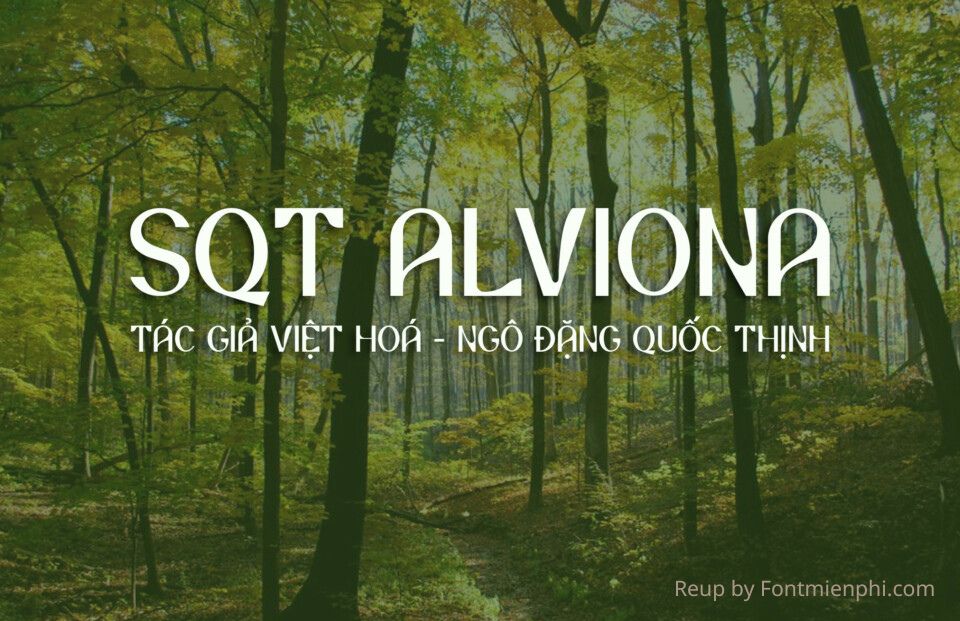
Font Việt hóa SQT Alviona Tải miễn phí font chữ thanh lịch, hiện đại
Font Việt hóa SQT Alviona – Tải miễn phí font chữ thanh lịch, hiện đại
Font Việt hóa SQT Alviona là một mẫu font chữ đẹp mang phong cách thanh lịch, mềm mại và hiện đại. Với đường nét tinh tế, kiểu dáng nổi bật và khả năng tạo điểm nhấn tốt, SQT Alviona rất phù hợp cho nhiều dự án thiết kế sáng tạo như logo, poster, banner, thiệp cưới, ảnh bìa, tiêu đề, bao bì sản phẩm và nội dung mạng xã hội.
Giới thiệu font SQT Alviona Việt hóa
SQT Alviona sở hữu phong cách chữ nghệ thuật, hiện đại nhưng vẫn giữ được nét mềm mại và sang trọng. Font tạo cảm giác nhẹ nhàng, tinh tế, phù hợp với các thiết kế cần sự nổi bật nhưng không quá cầu kỳ.
Phiên bản font Việt hóa đã được bổ sung hệ thống ký tự tiếng Việt, giúp người dùng dễ dàng nhập đầy đủ dấu và sử dụng trong các phần mềm thiết kế phổ biến.
Font có thể phù hợp với nhiều chủ đề như:
• Thiết kế logo thương hiệu
• Thiết kế poster và banner
• Làm thiệp cưới, thiệp mời
• Thiết kế ảnh bìa Facebook, YouTube
• Làm tiêu đề video và thumbnail
• Thiết kế bao bì sản phẩm
• Làm nội dung thời trang, mỹ phẩm, làm đẹp
• Thiết kế bài đăng mạng xã hội
• Làm typography và các ấn phẩm sáng tạo
Điểm nổi bật của font Việt hóa SQT Alviona
Một trong những ưu điểm nổi bật của font SQT Alviona là kiểu dáng dễ tạo ấn tượng ngay từ cái nhìn đầu tiên. Các đường nét của font mang tính thẩm mỹ cao, thích hợp để sử dụng làm tiêu đề hoặc điểm nhấn chính trong thiết kế.
Bên cạnh đó, phiên bản Việt hóa giúp font hiển thị tốt các ký tự tiếng Việt như ă, â, ê, ô, ơ, ư, đ cùng toàn bộ hệ thống dấu thanh. Nhờ vậy, người dùng có thể sử dụng font thuận tiện hơn trong các dự án thiết kế bằng tiếng Việt.
Một số ưu điểm của font gồm:
• Kiểu chữ thanh lịch và hiện đại
• Đường nét mềm mại, dễ tạo điểm nhấn
• Hỗ trợ gõ tiếng Việt
• Phù hợp với nhiều phong cách thiết kế
• Dễ sử dụng trong các phần mềm đồ họa
• Thích hợp cho cả thiết kế online và in ấn
Font SQT Alviona phù hợp với những thiết kế nào?
Font Việt hóa SQT Alviona đặc biệt phù hợp với những thiết kế cần thể hiện sự sang trọng, nữ tính, sáng tạo hoặc tinh tế. Bạn có thể sử dụng font cho các thương hiệu thời trang, mỹ phẩm, studio, spa, nhiếp ảnh, đồ handmade hoặc sản phẩm cao cấp.
Ngoài ra, font cũng phù hợp để làm tiêu đề cho bài viết, banner quảng cáo, ảnh giới thiệu sản phẩm, bảng giá, menu, thiệp chúc mừng và các nội dung truyền thông trên mạng xã hội.
Để thiết kế đạt hiệu quả tốt nhất, bạn nên sử dụng SQT Alviona cho những đoạn chữ ngắn, tên thương hiệu, slogan hoặc tiêu đề lớn. Với nội dung dài, nên kết hợp font này cùng một font chữ đơn giản để đảm bảo khả năng đọc.
• Phong cách: Thanh lịch, mềm mại, hiện đại
• Ứng dụng: Logo, poster, banner, thiệp cưới, tiêu đề, bao bì và mạng xã hội
Kết luận
Font Việt hóa SQT Alviona là lựa chọn phù hợp dành cho những ai đang tìm kiếm một font chữ đẹp, thanh lịch và dễ tạo điểm nhấn. Với khả năng hỗ trợ tiếng Việt cùng phong cách mềm mại, hiện đại, font có thể ứng dụng hiệu quả trong nhiều dự án thiết kế khác nhau.